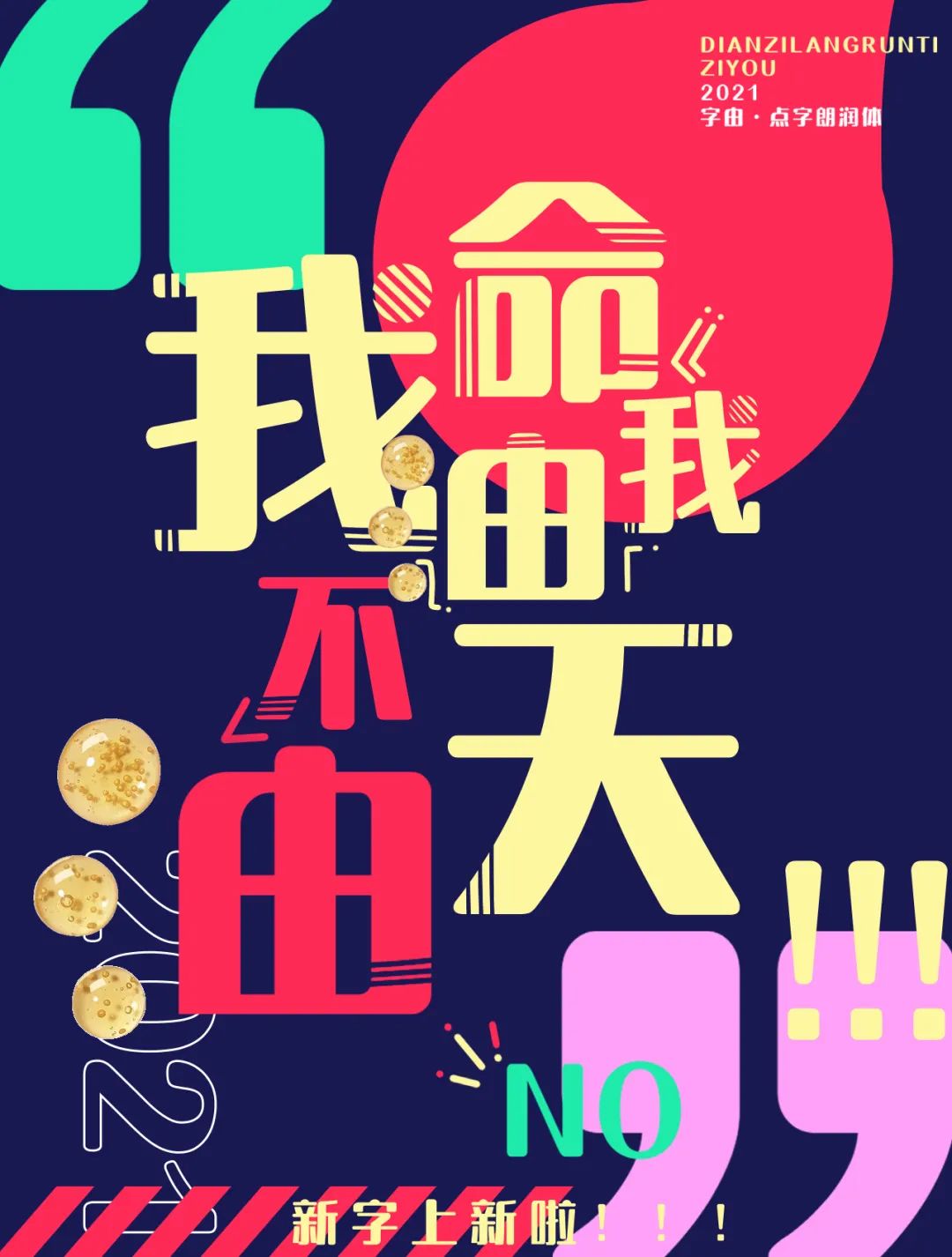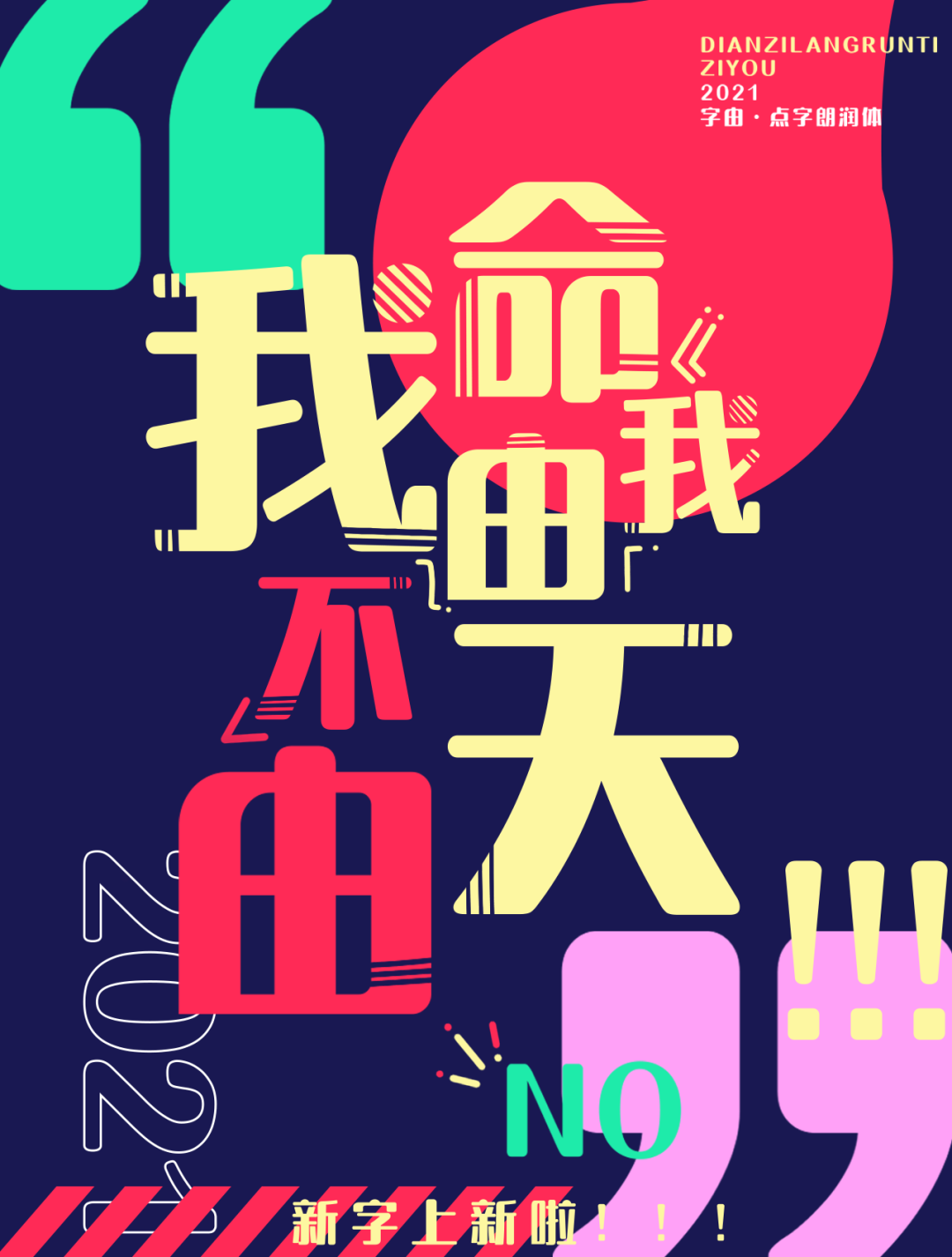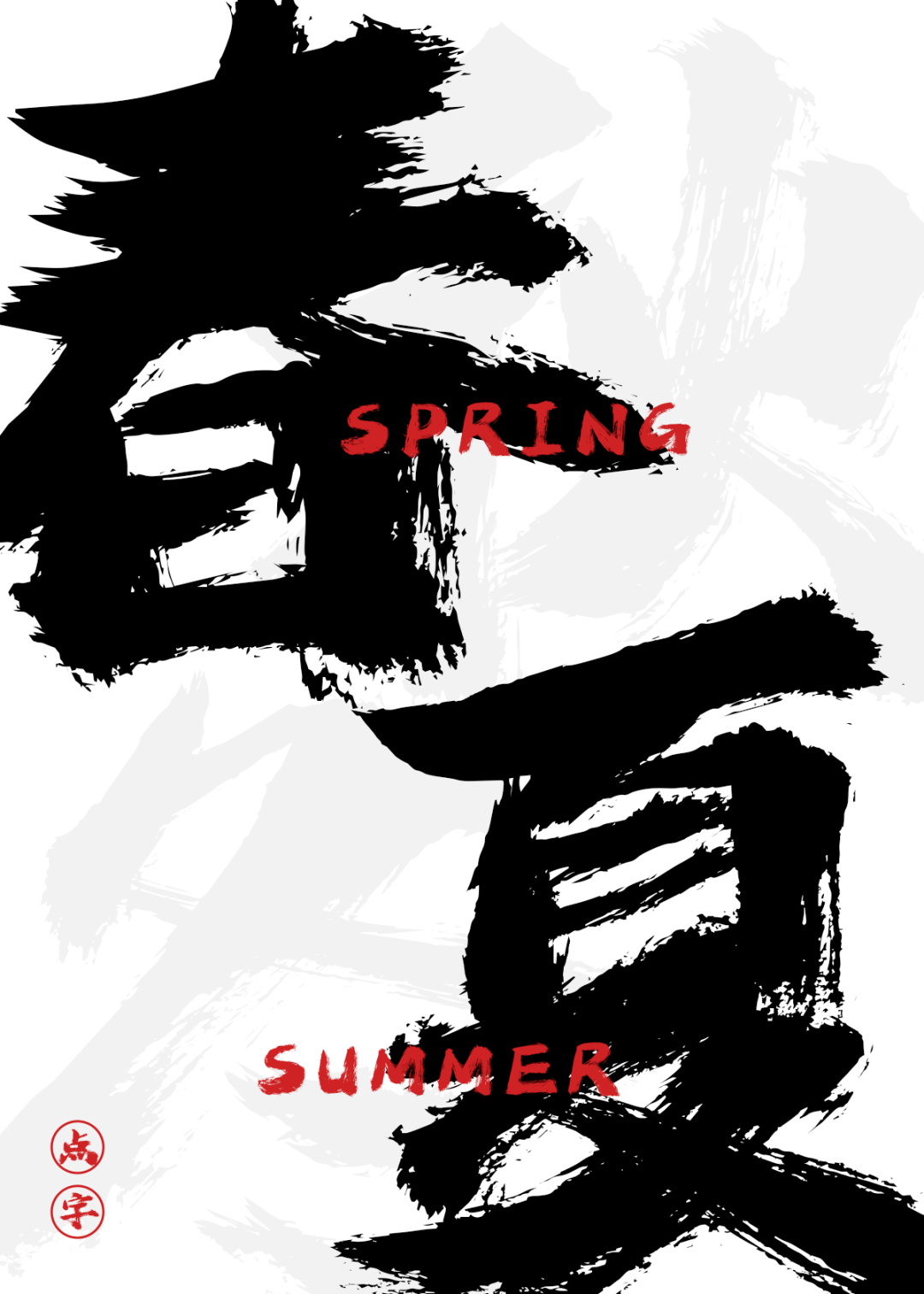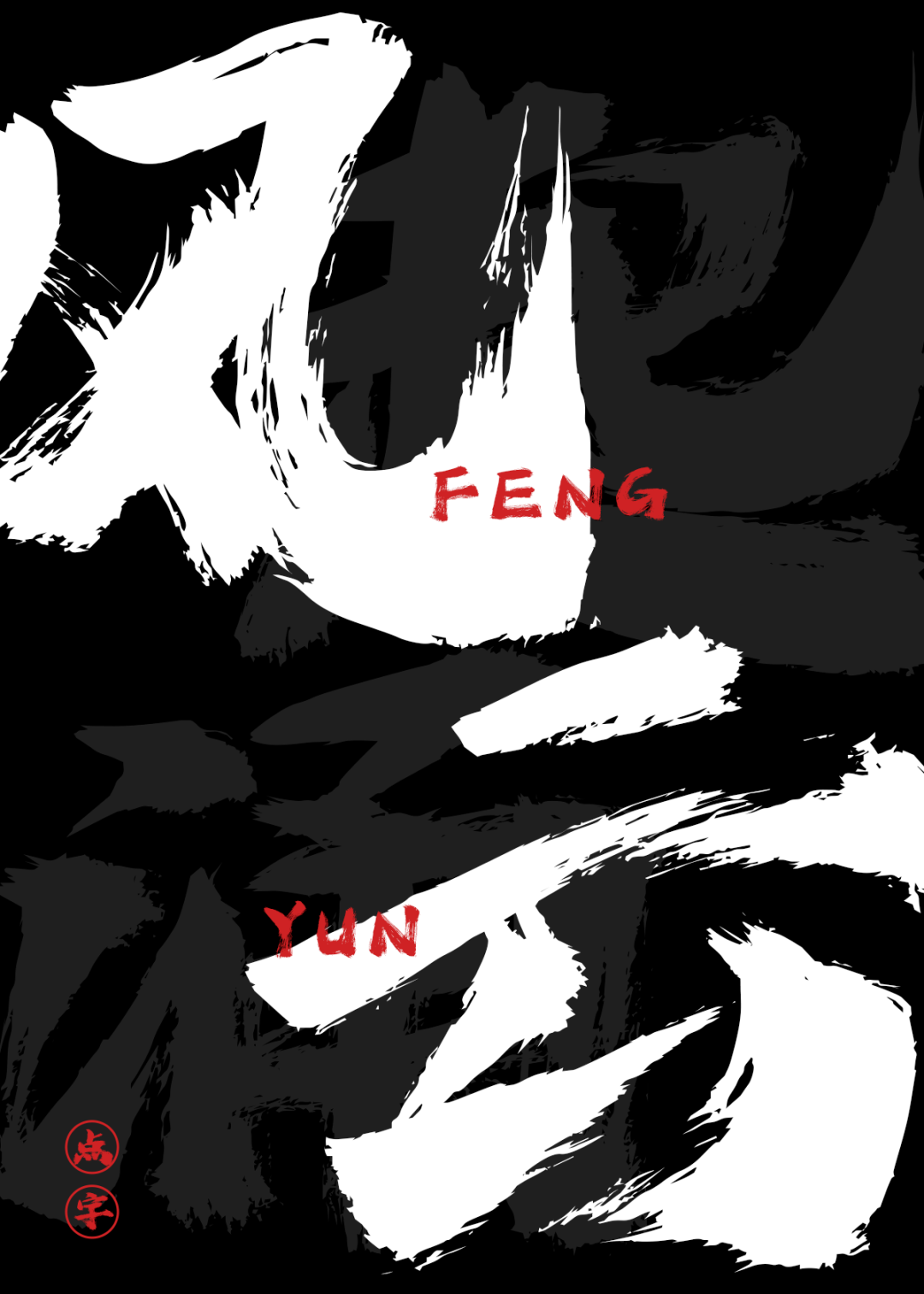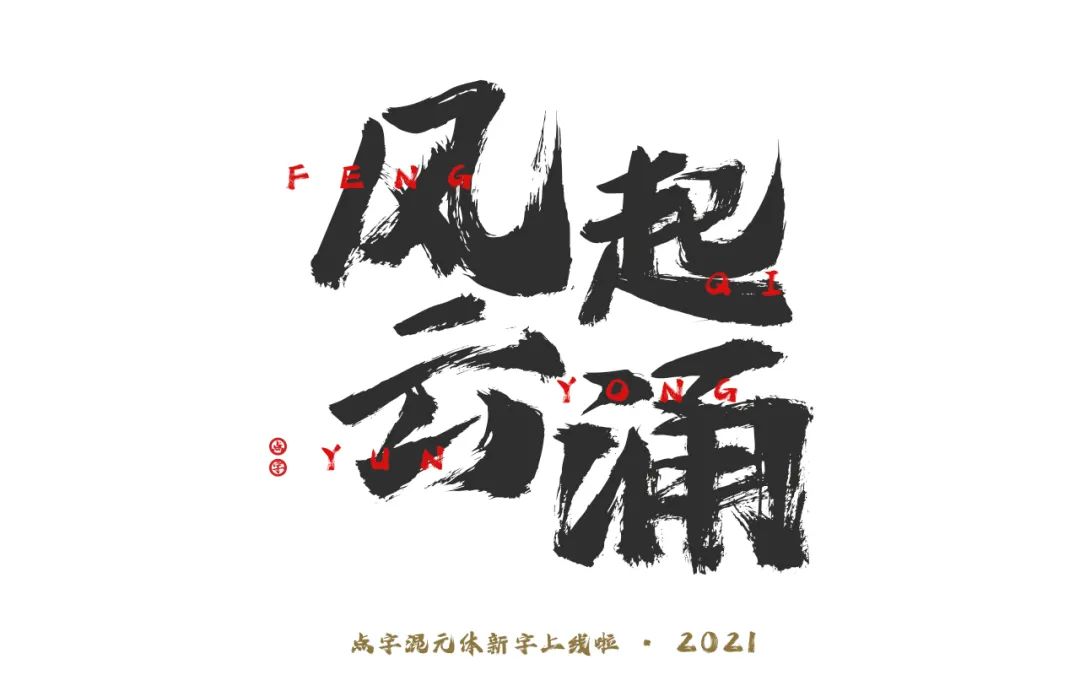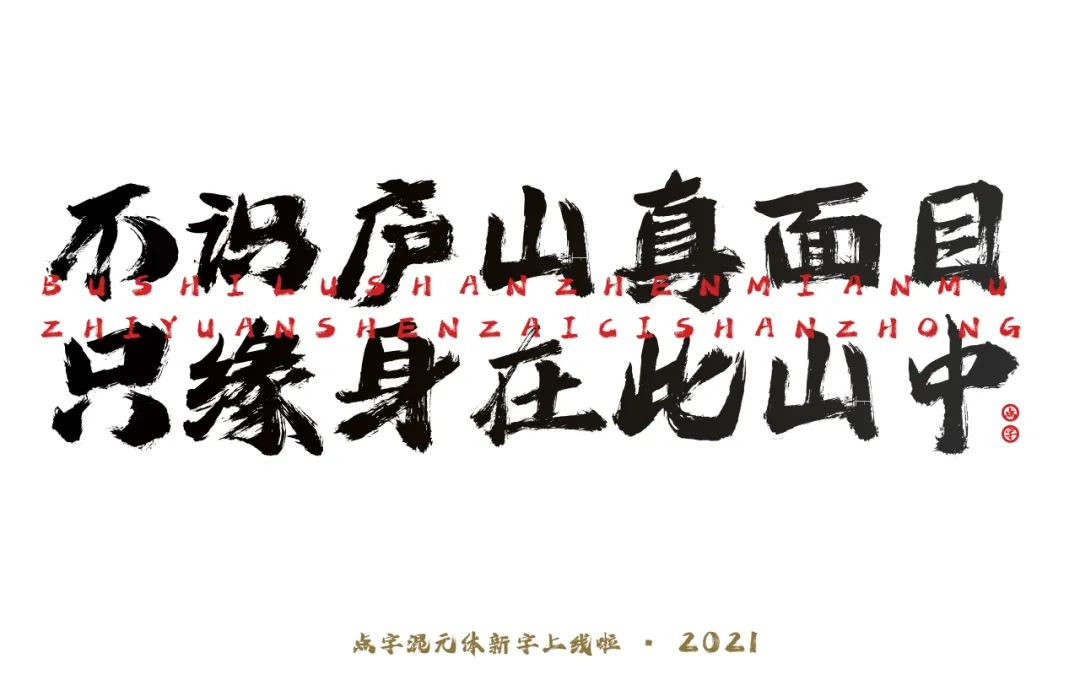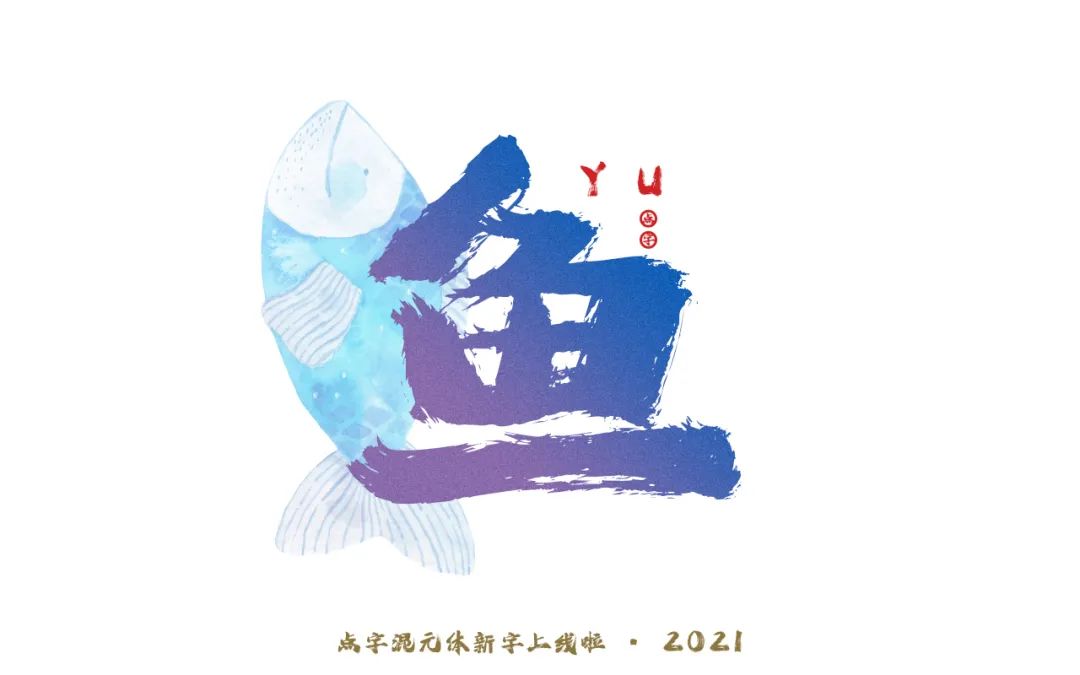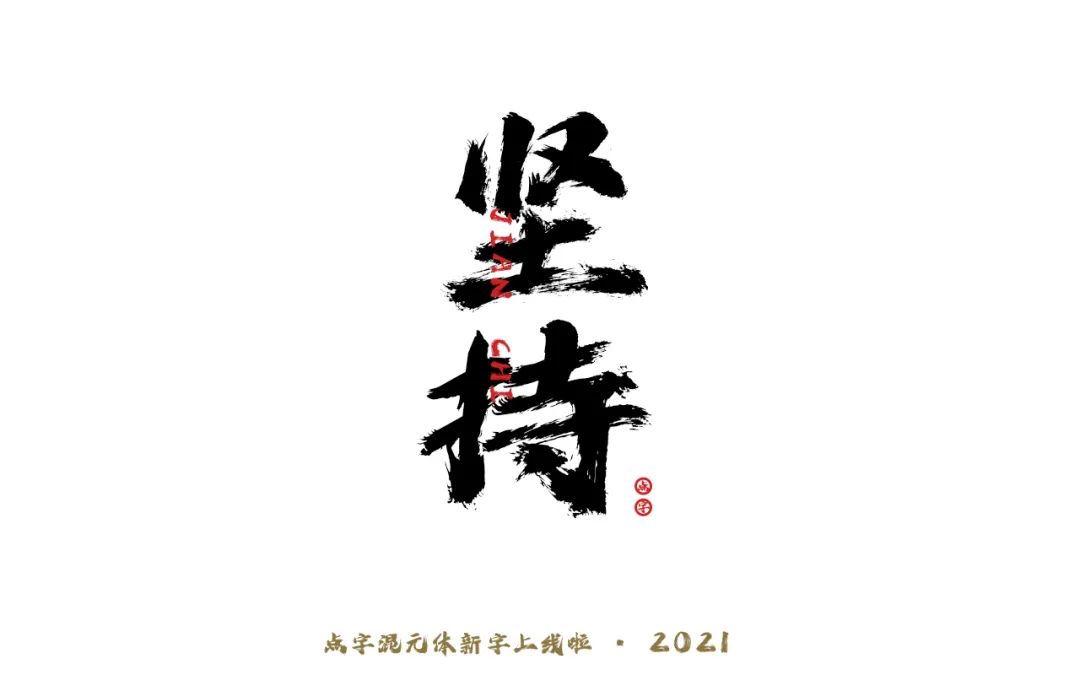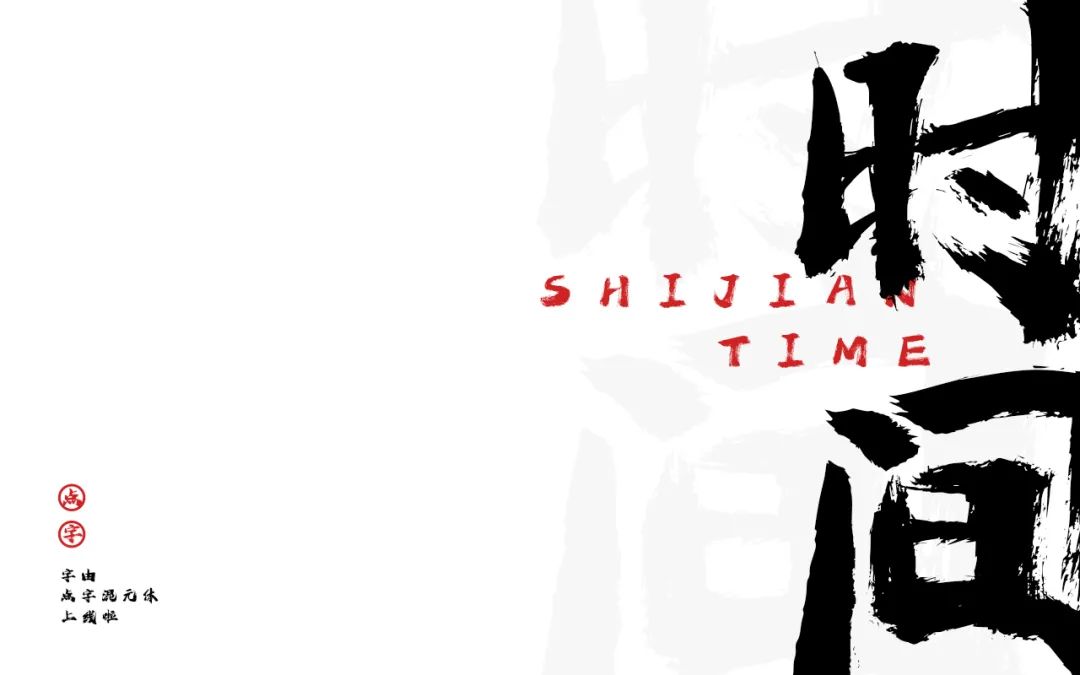
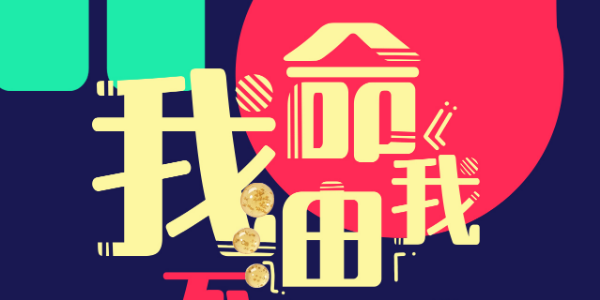
有了这几款字体,我字由我不由天!
“烈金”的好兄弟
点字烈金体,你应该不陌生吧?看起来特别飒!
但这种锋芒毕露的字体,一个怎么够用,所以它的好兄弟——点字混元体又横空出世了!
跟烈金的尖锐不一样,混元采用的是豪放、随意、粗犷的笔法,特别适合冲击力强的海报。
装饰体yyds
如果你是字由会员的铁粉,肯定能随口说出那些好用的装饰体,比如点字综艺体、点字奇妙体、点字匹喏曹、点字墩墩体,还有新上的点字朗润体。
它们都有一个共同的特点,就是经典又耐用,无论放在哪个画面上都好看,特别适合选字困难症用户。
最后,要特别给点字库撒花,因为它出了首款西文字体——IdeaFonts Ranger